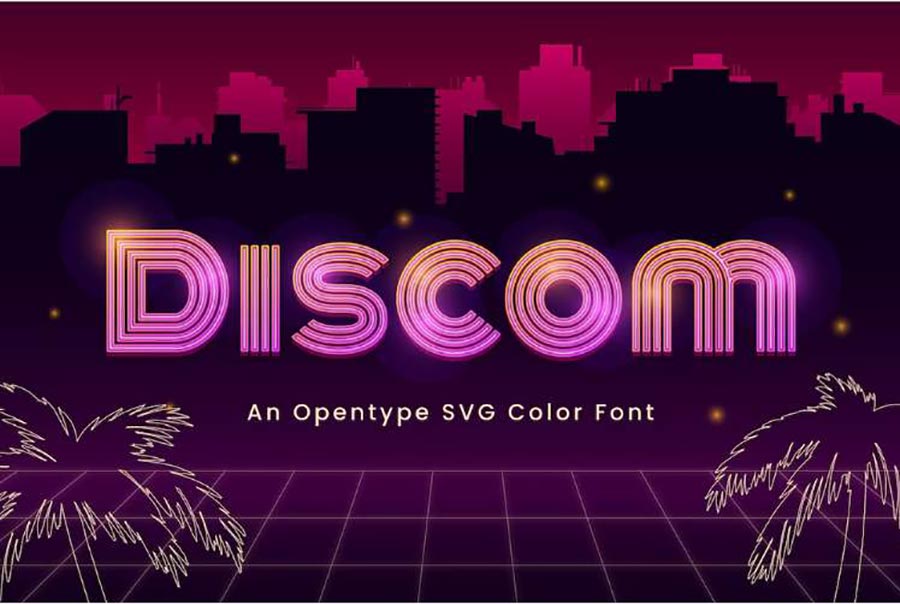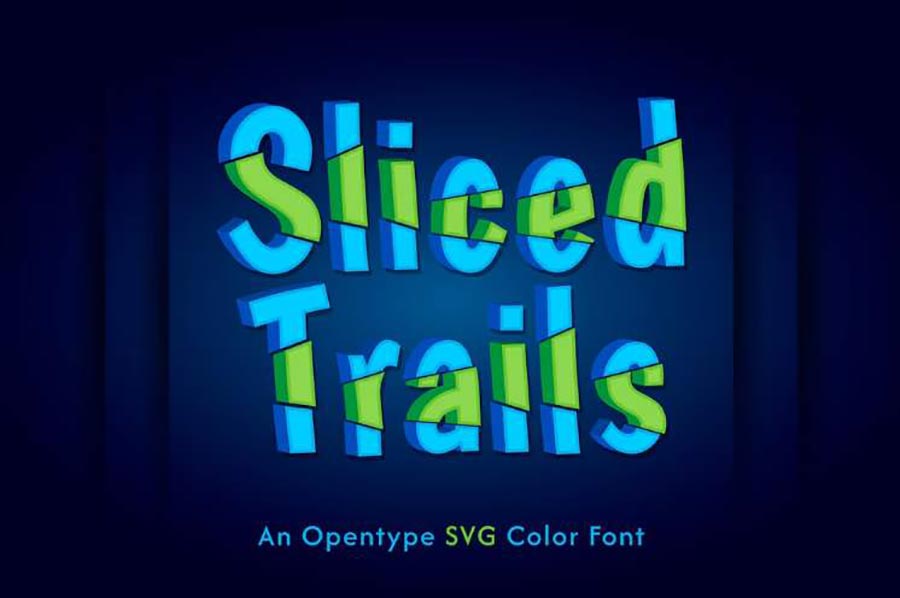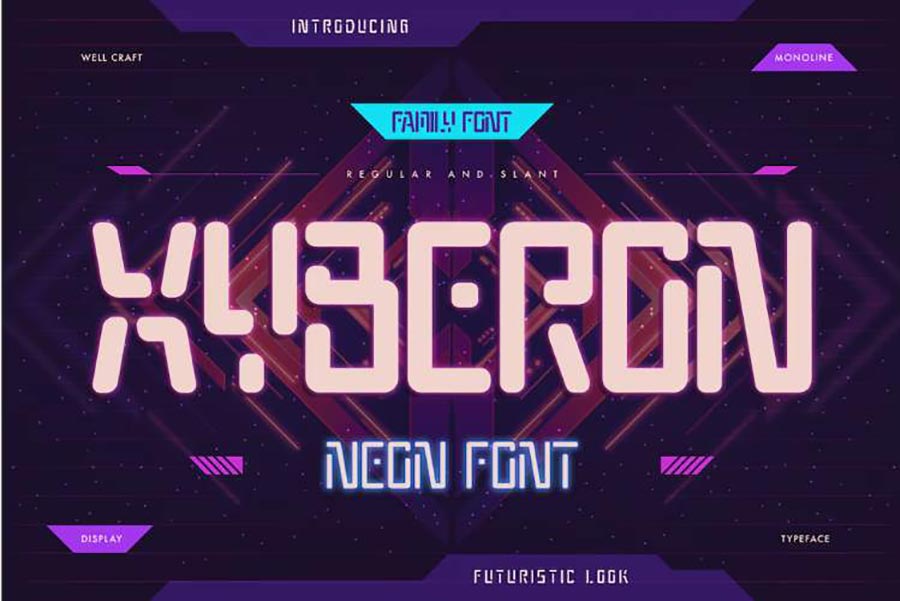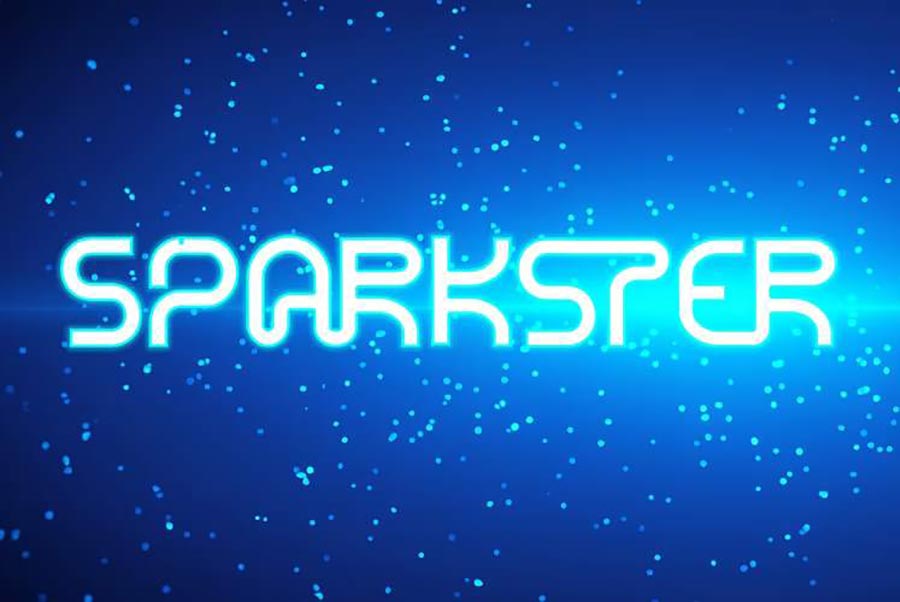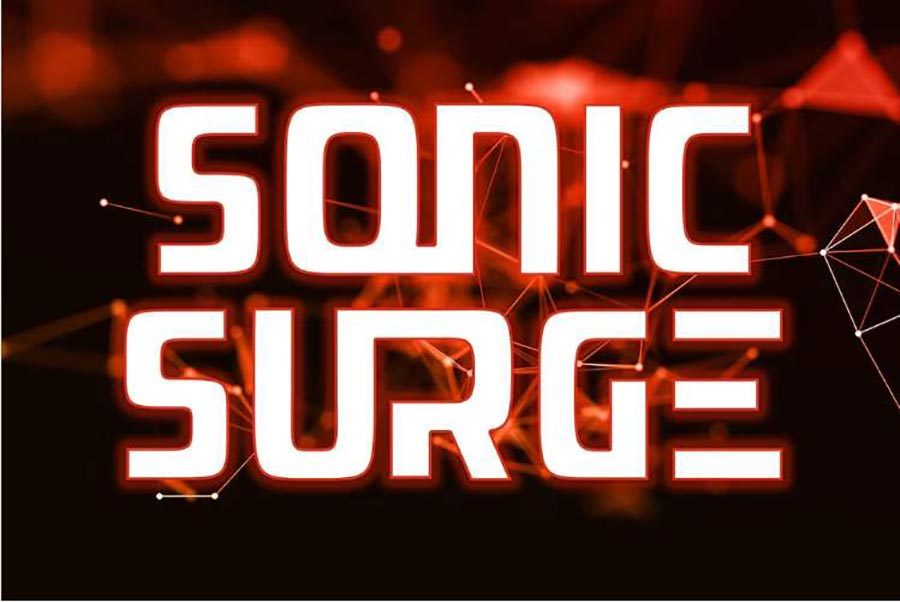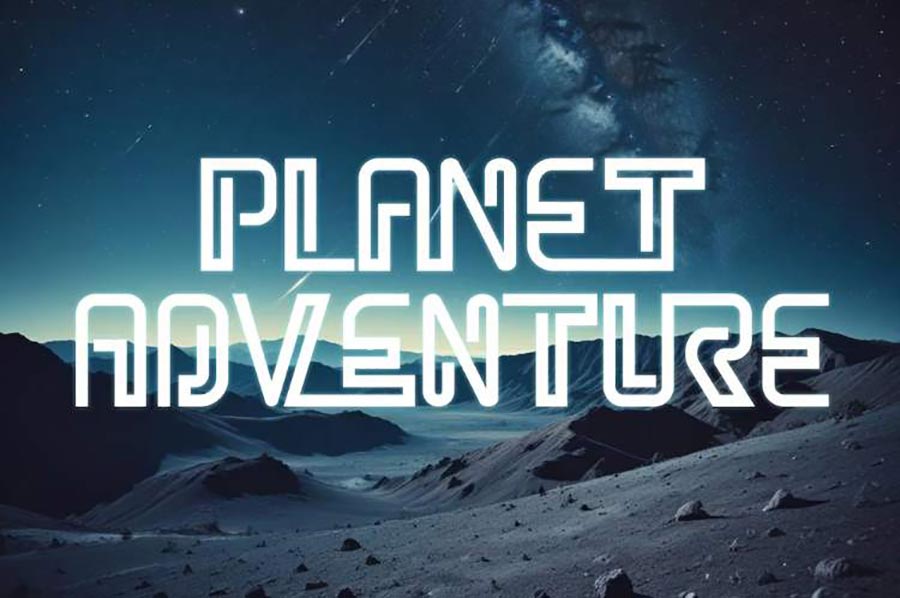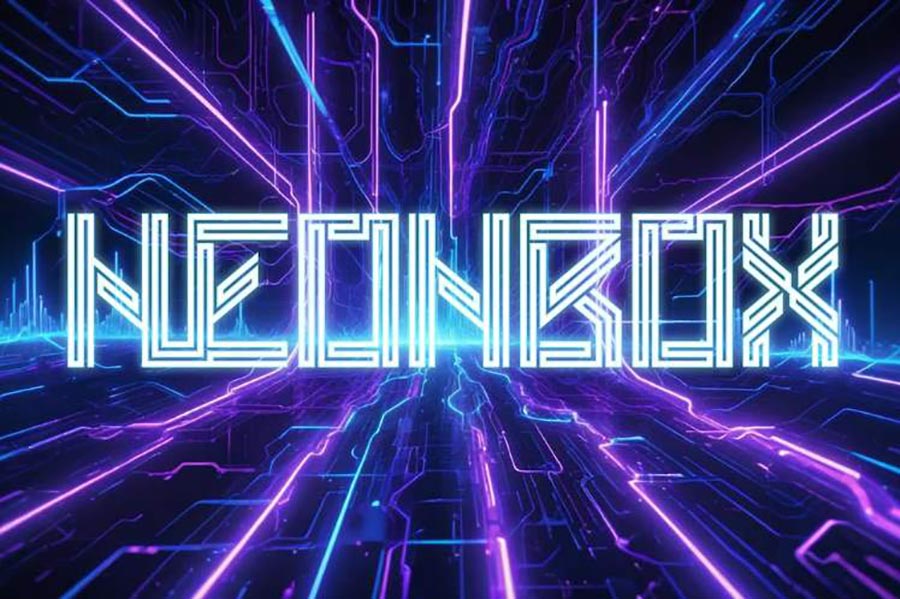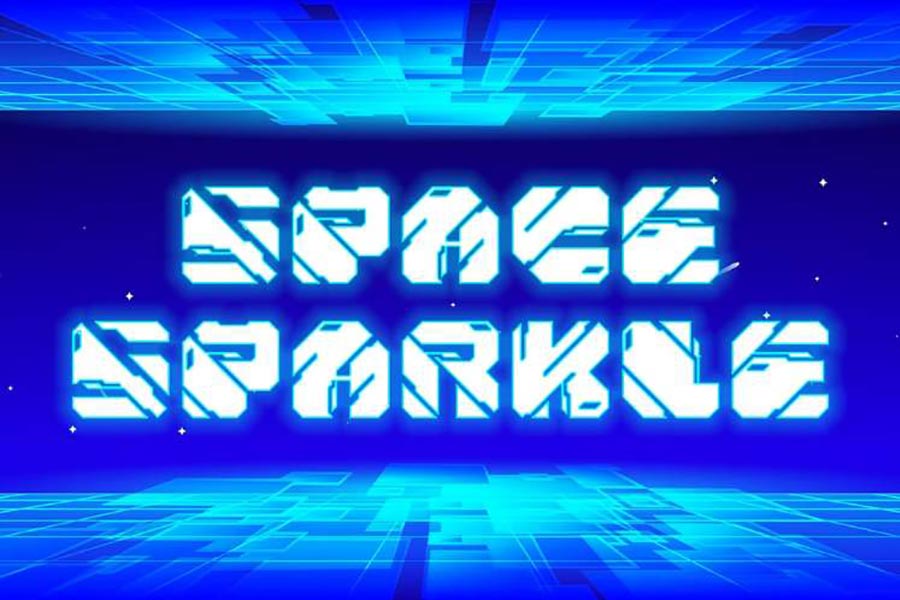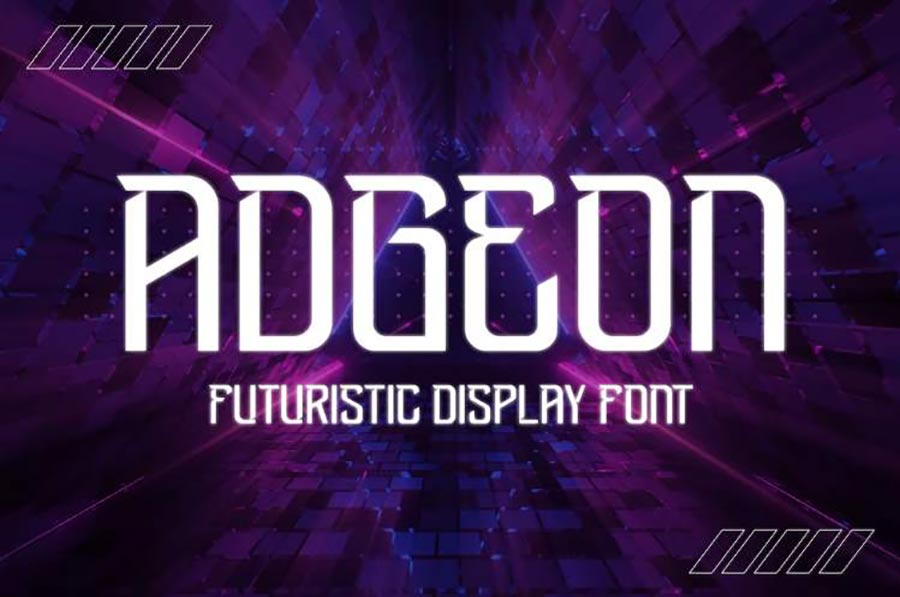
Hướng Dẫn Tải Fonts Neon Cực Đẹp Miễn Phí
Trong thiết kế đồ họa, việc lựa chọn đúng font chữ có thể tạo ra sự khác biệt lớn trong việc truyền tải thông điệp và cảm xúc của một dự án. Đặc biệt, fonts neon với sự nổi bật và hiện đại đang trở thành xu hướng trong nhiều thiết kế sáng tạo. Bài viết này sẽ hướng dẫn bạn cách tải các fonts neon miễn phí một cách dễ dàng và hiệu quả.
Trước khi tải bất kỳ font nào, hãy xác định rõ mục đích sử dụng của bạn. Fonts neon thường được sử dụng trong các thiết kế biển quảng cáo, poster sự kiện, hoặc các sản phẩm truyền thông cần sự nổi bật. Việc xác định nhu cầu sẽ giúp bạn chọn được font phù hợp nhất.
Fonts neon mang lại một luồng gió mới cho các thiết kế hiện đại, giúp chúng trở nên nổi bật và cuốn hút hơn. Với hướng dẫn trên, hy vọng bạn sẽ tìm được những fonts neon đẹp mắt và phù hợp nhất cho dự án của mình. Chúc bạn thành công.